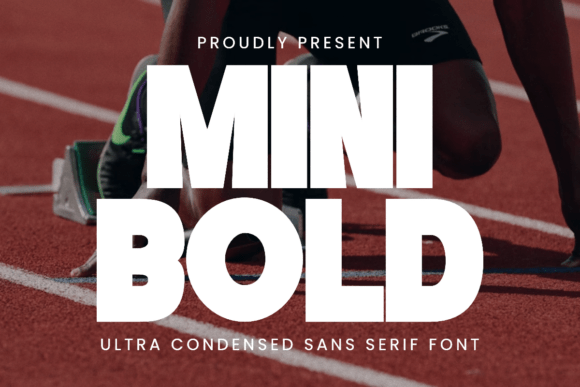
Mini Bold
Mini Bold : La Police Qui Donne du Gagner à Votre Design
Mini Bold est une police ultra-condensée sans-serif qui combine puissance, énergie et modernité. Grâce à ses formes de lettres hautes et audacieuses, elle apporte un impact visuel fort à chaque projet. Que vous créiez un poster, un logo sportif, une bannière publicitaire ou un design d’apparel, Mini Bold rend vos messages lisibles et mémorables.
Pourquoi Mini Bold est la Police Parfaite pour la Communication Visuelle
- Impact immédiat : Ses caractères massifs et ses formes condensées attirent le regard en un clin d’œil.
- Lisibilité maximale : La structure sans-serif élimine les distractions, offrant une lecture fluide même à grande distance.
- Polyvalence de style : Parfait pour les affiches, les titres de magazine, les logos de marques sportives, et les campagnes publicitaires.
- Compatibilité moderne : Conçue pour s’intégrer naturellement aux designs contemporains et aux interfaces digitales.
- Forte présence visuelle : Idéal pour les projets nécessitant une présence forte, comme les vêtements, les panneaux d’affichage, ou les campagnes de branding.
Applications Pratiques de Mini Bold
Posters & Affiches – Sa structure condensée permet d’intégrer plus de texte sans sacrifier la lisibilité, idéal pour les événements sportifs ou les campagnes de sensibilisation.
Design d’Apparel – Les formes épaisses et nettes se lisent sur les logos de t-shirts, sweatshirts et accessoires, donnant une allure athlétique et moderne.
Branding & Logos – L’énergie de Mini Bold rend les logos dynamiques et mémorables, parfaits pour les marques qui veulent se démarquer.
Publicité & Marketing Digital – Les titres accrocheurs et les call‑to‑action se démarquent dans les bannières, les affiches en ligne et les présentations numériques.
Conseils d’Intégration pour Designers
- Utilisez une hauteur de ligne de 1,2 à 1,4 pour conserver une bonne densité visuelle.
- Combinez Mini Bold avec une police fine ou régulière pour créer un contraste typographique.
- Assurez une couleur noire ou très sombre sur des fonds clairs pour maximiser la lisibilité.
- Expérimentez avec des effets de surbrillance numériques ou des ombres portées pour renforcer l’impact.
Conclusion
Mini Bold est plus qu’une simple police ; c’est un outil de communication qui transforme chaque projet en une déclaration visuelle forte. Sa combinaison unique de condensation, de puissance et de modernité en fait une ressource incontournable pour les designers qui recherchent l’impact sans compromis. Intégrez Mini Bold dès aujourd’hui et voyez votre design atteindre de nouveaux sommets.